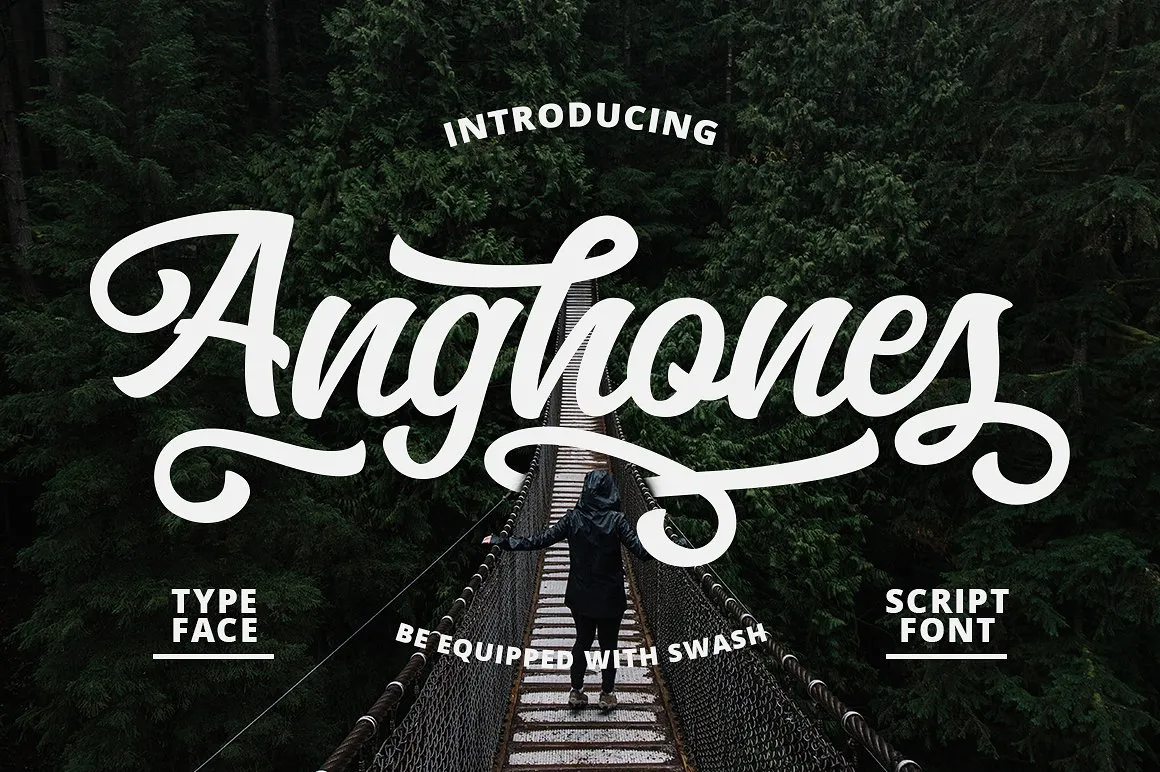
Anghones Script Font – Download Grátis
Anghones Script Font é uma escolha perfeita para designers que desejam adicionar um toque moderno e elegante a suas criações. Introduzida pela maculinc, este tipo de letra script possui características simples e legíveis, tornando-o confortável para uso em diversos ambientes design. A sua escrita fluida é particularmente adequada para criar mensagens interessantes, adaptadas à sua preferência pessoal. Anghones pode ser facilmente utilizado em uma variedade de aplicativos como logos, estímulos promocionais, embalagens, headlines, cartazes, camisetas e roupas, cartões de presentes para a empresa, cartões de aniversário e até mesmo convites de casamento. A sua natureza fluida torna-a ideal para uso em uma ampla gama de projetos gráficos, tornando o Anghones Script Font uma fonte que se destaca não apenas pela sua aparência única, mas também pelo seu vasto campo de aplicabilidade.